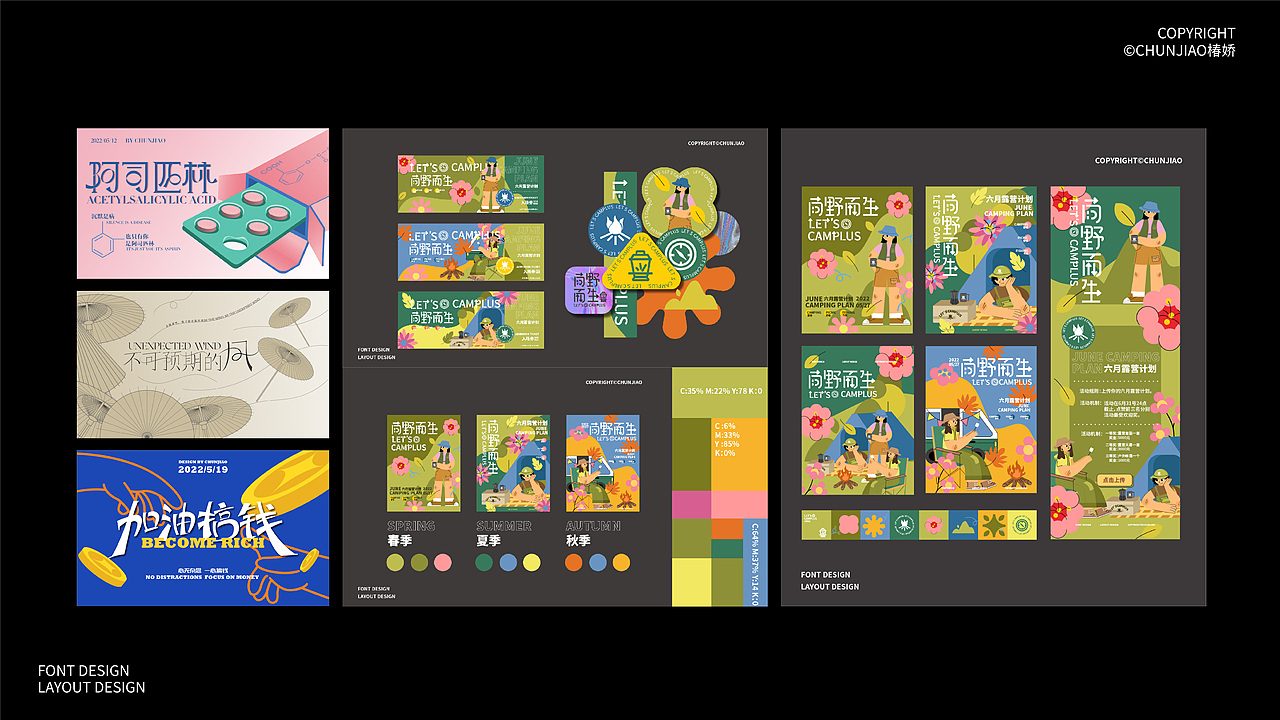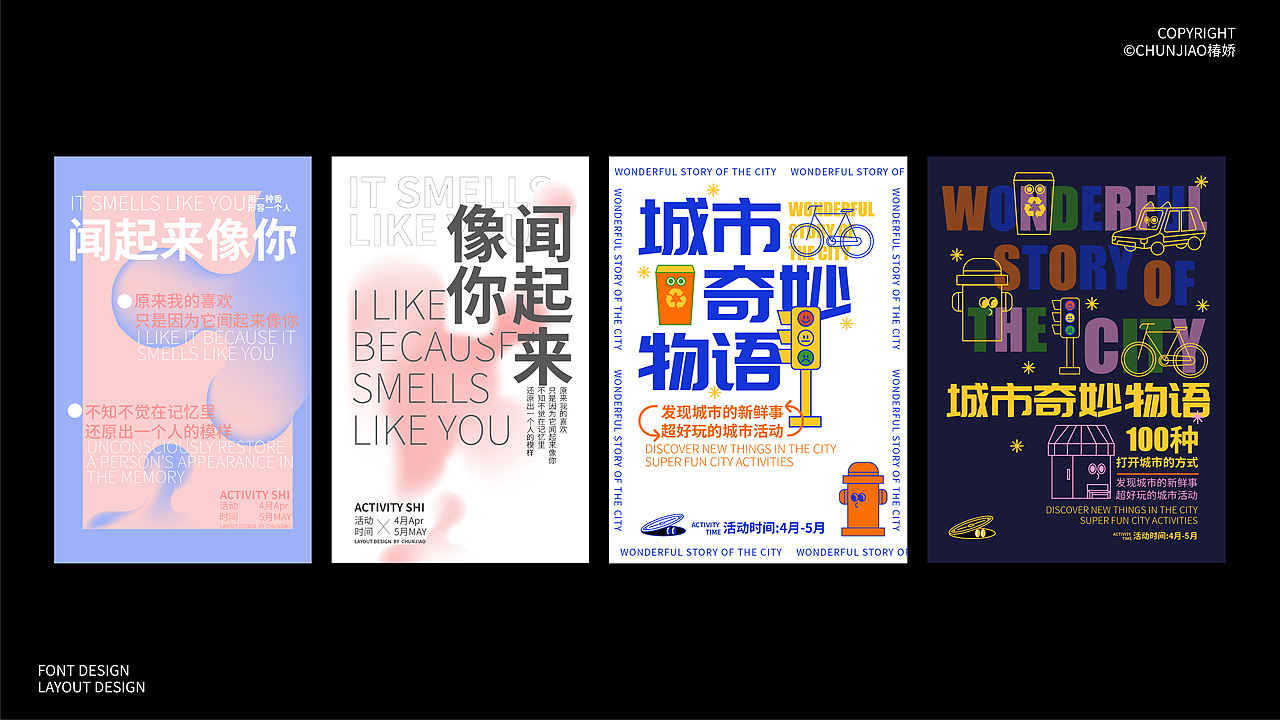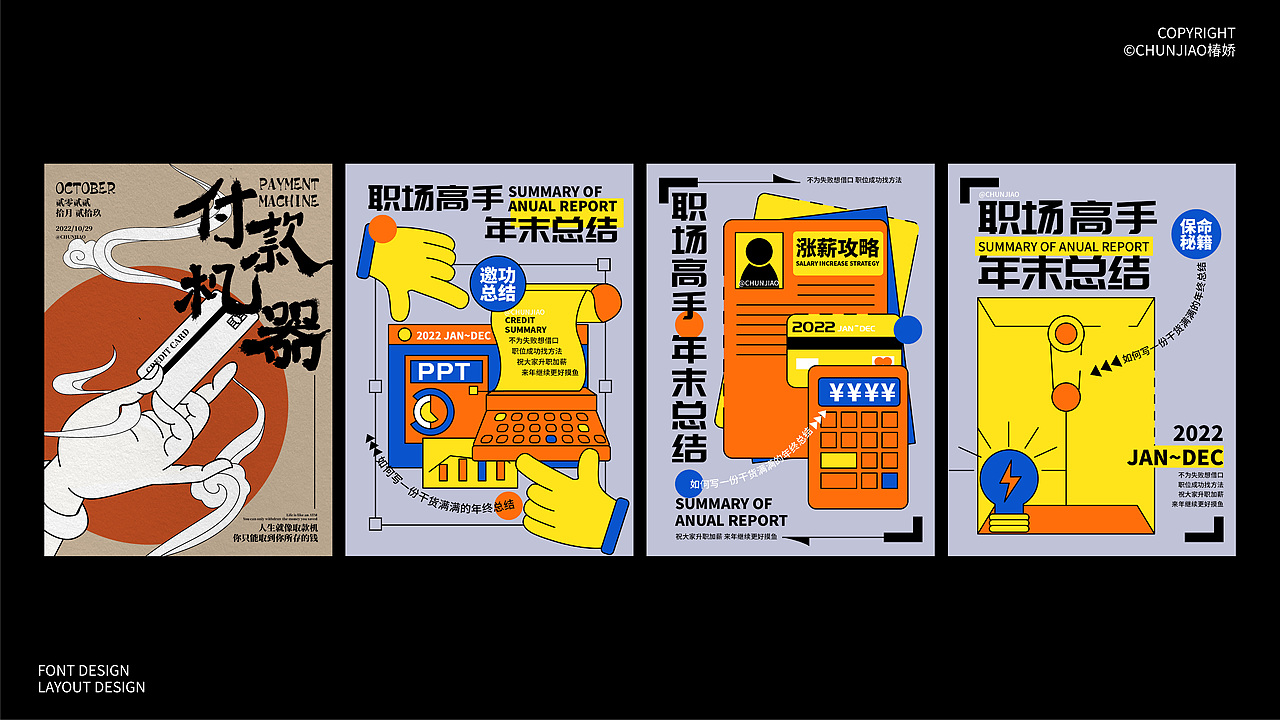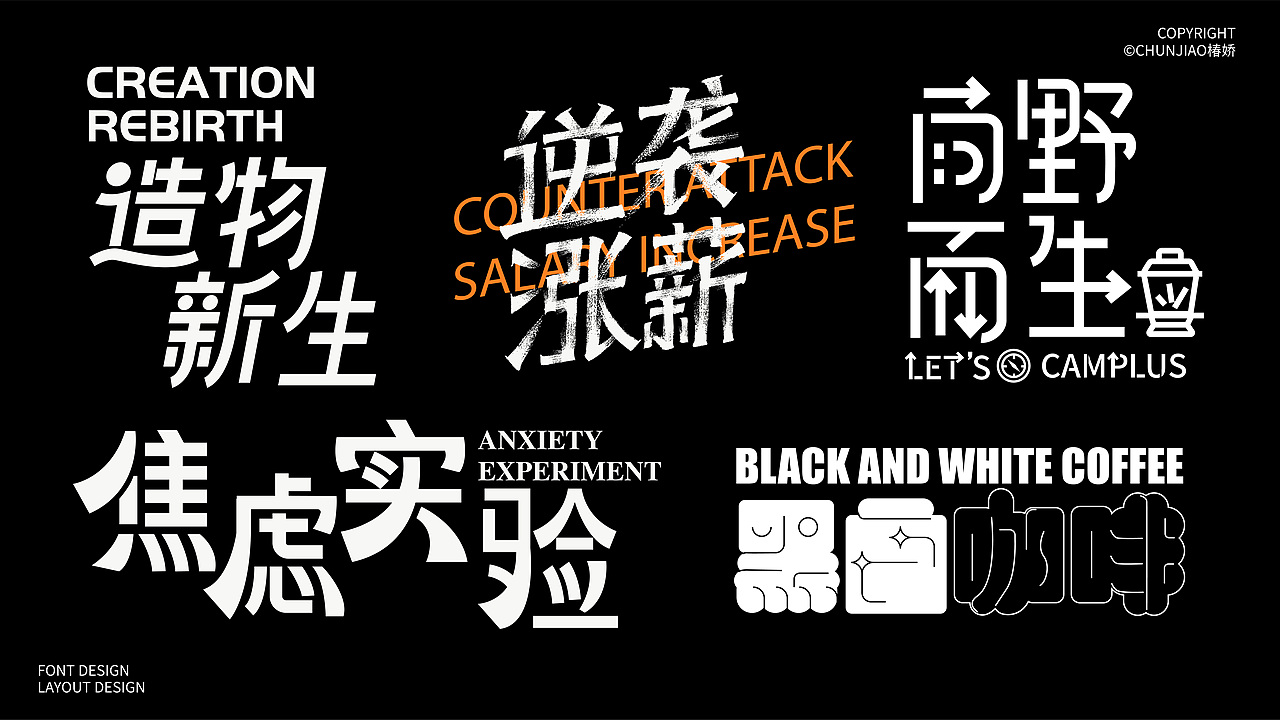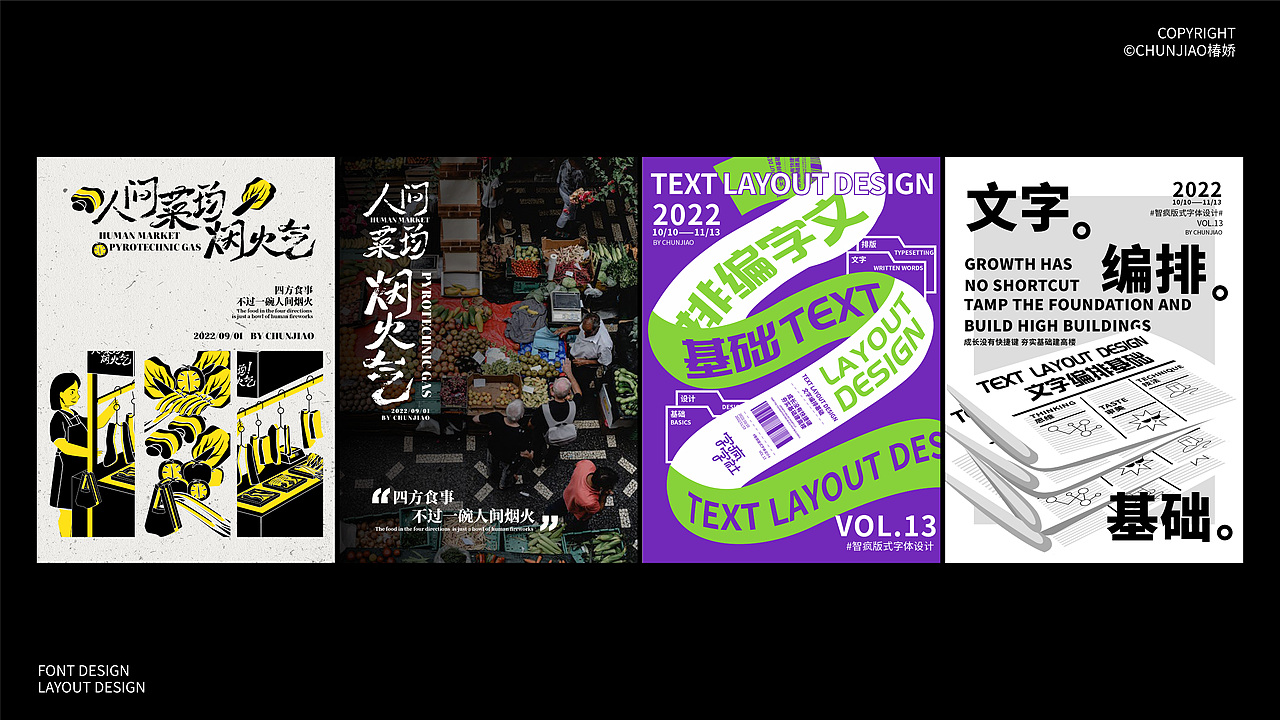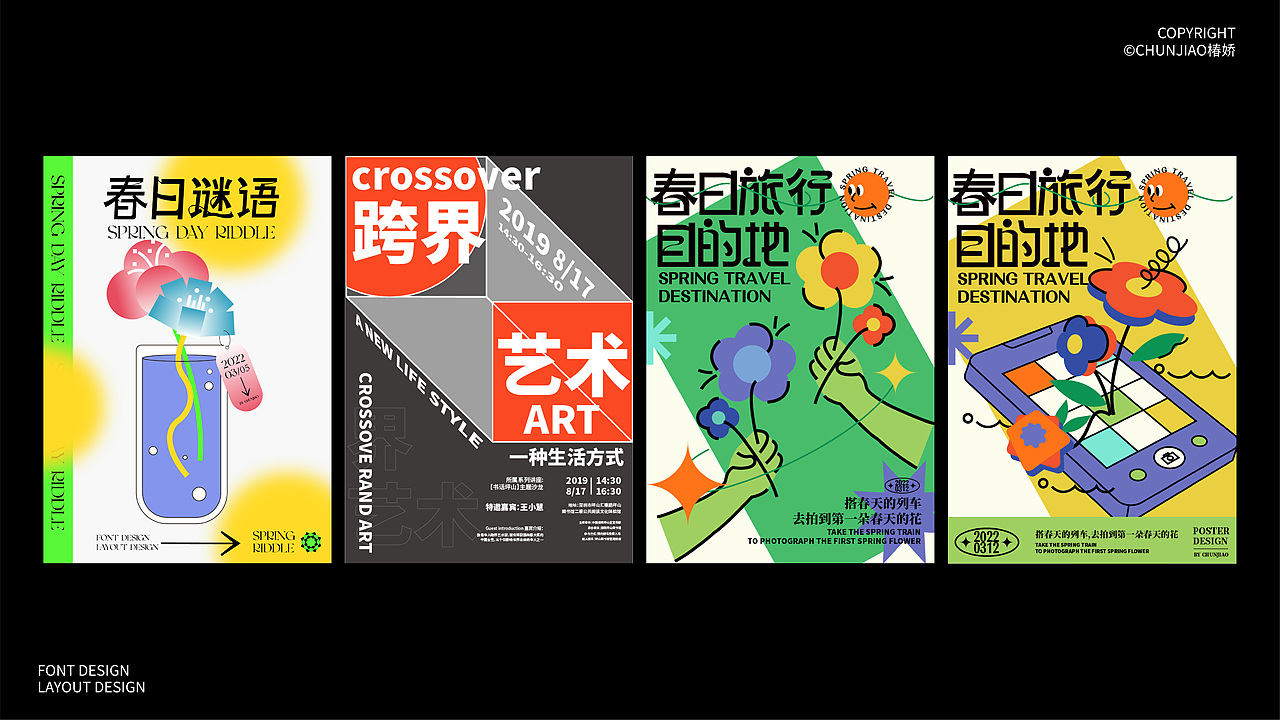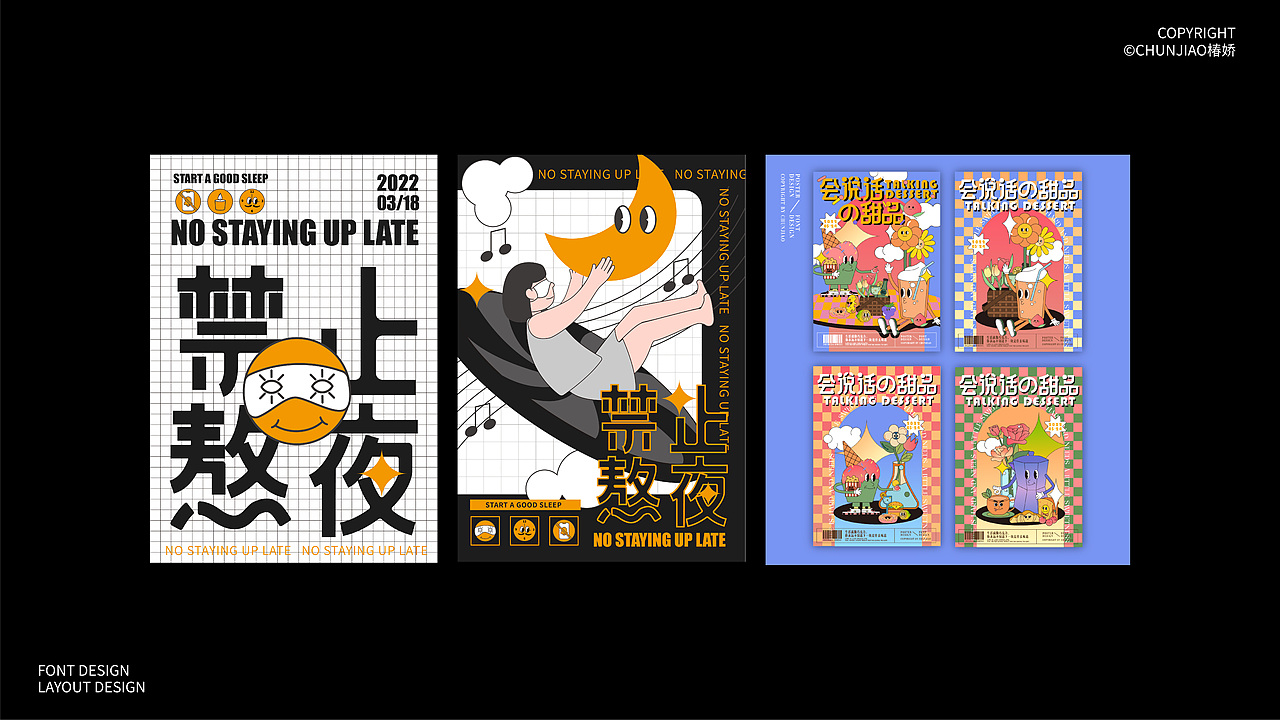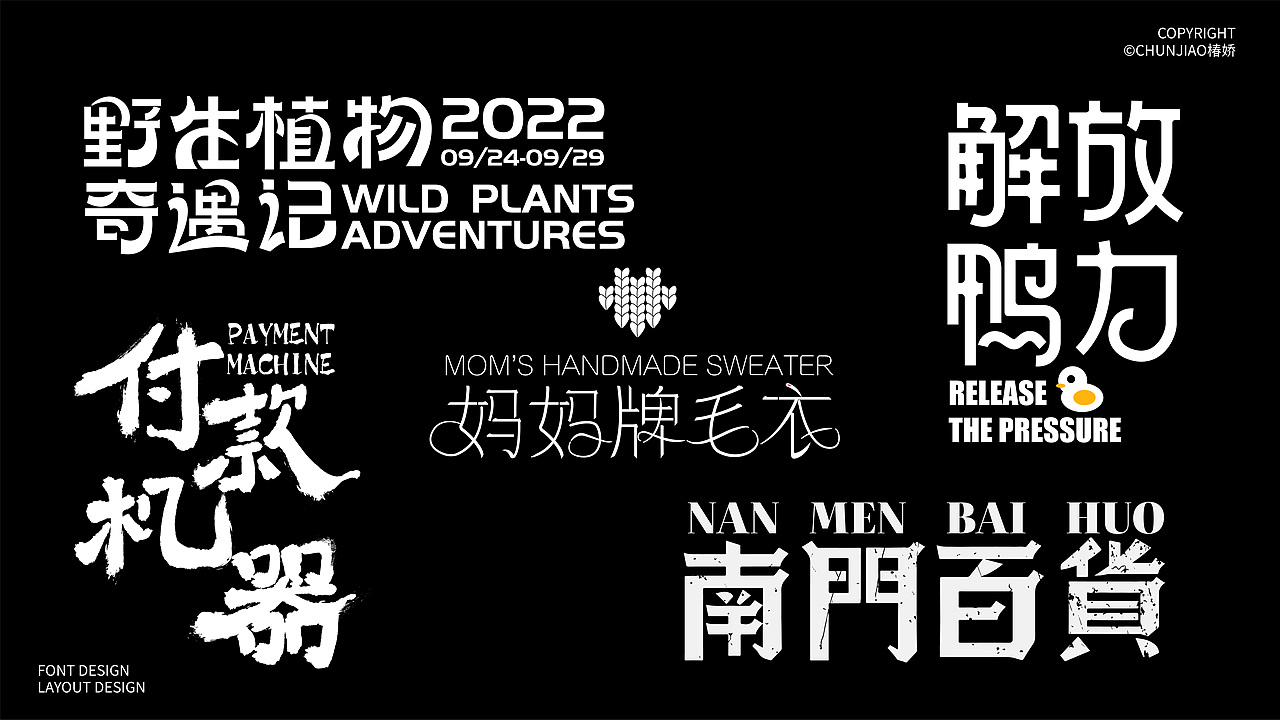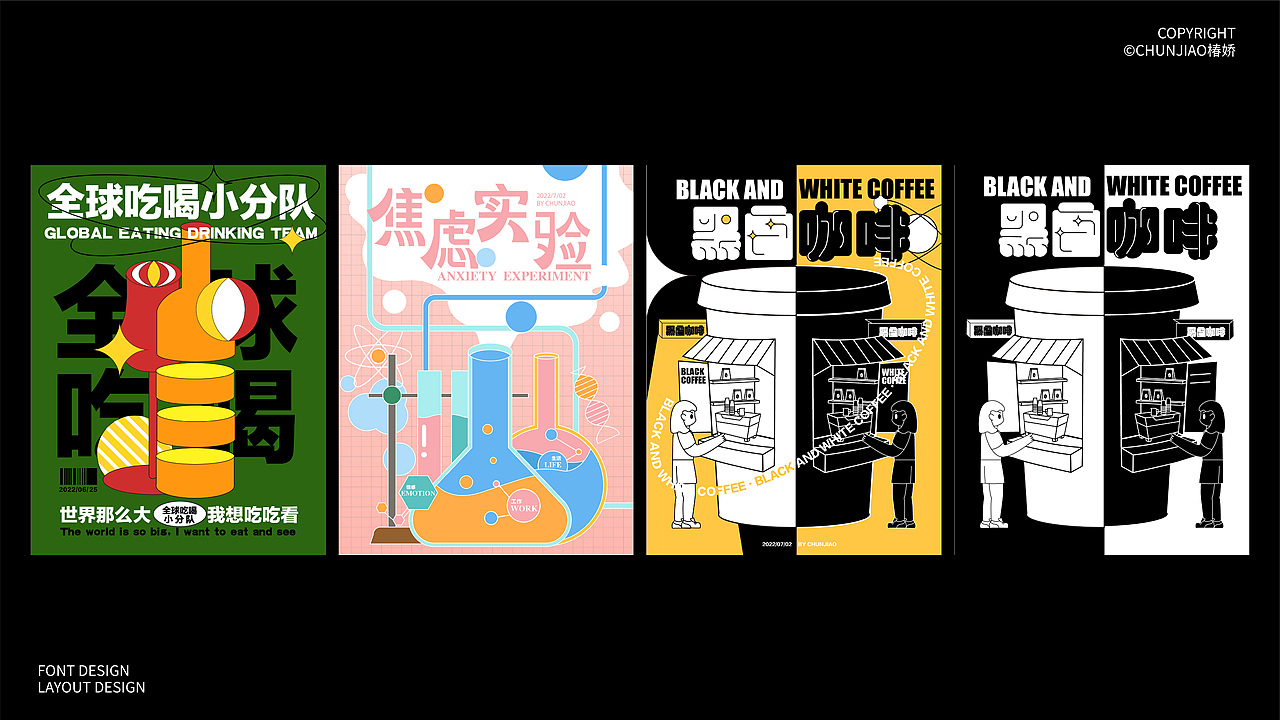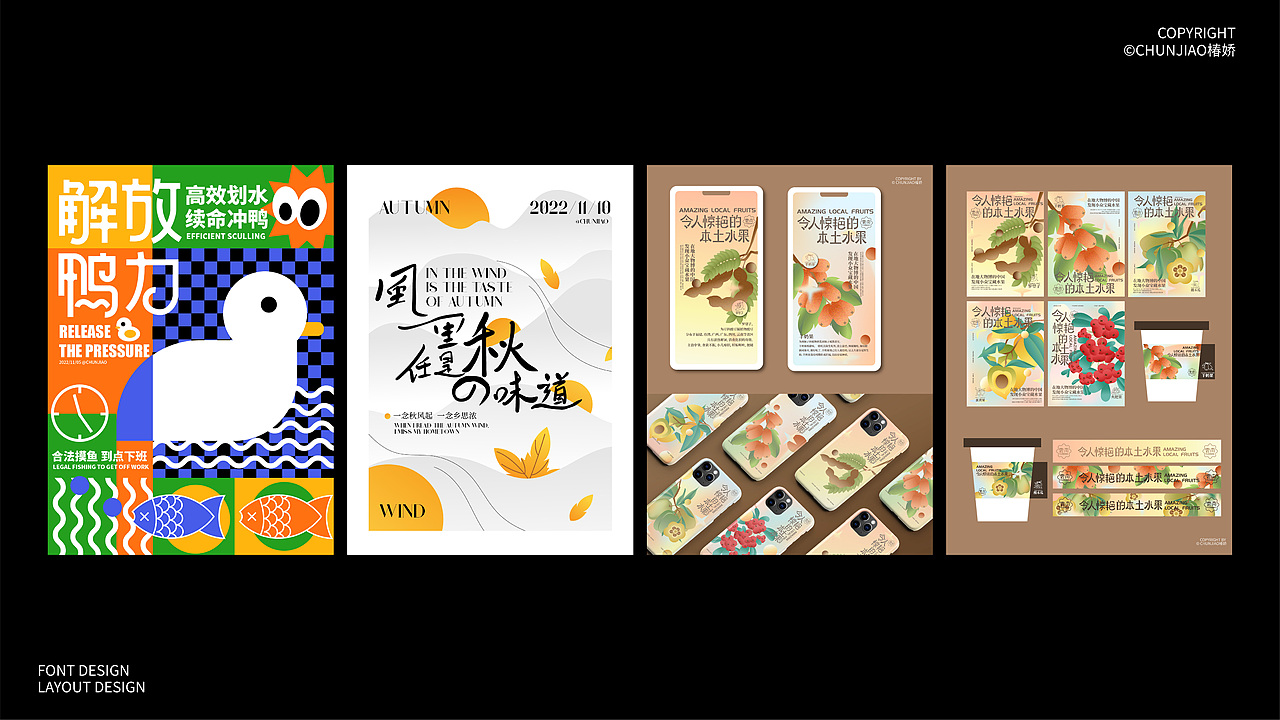
2022字体与版式设计总结
亲爱的朋友们2022已经过去,潦草的总结一下这一年的非商业作品。
在字体设计上,手写字体和书法字体依旧很烂,人有时候就是有惰性,会以自己最熟悉快捷的方式去做一个任务。
每一个主KV视觉的作业都单独发过,其实个人最爱的是《仿生盆栽》和《邻人惊艳的本土水果》,
总之每年都有新的目标和新的学习,希望大家都依旧喜欢做设计。